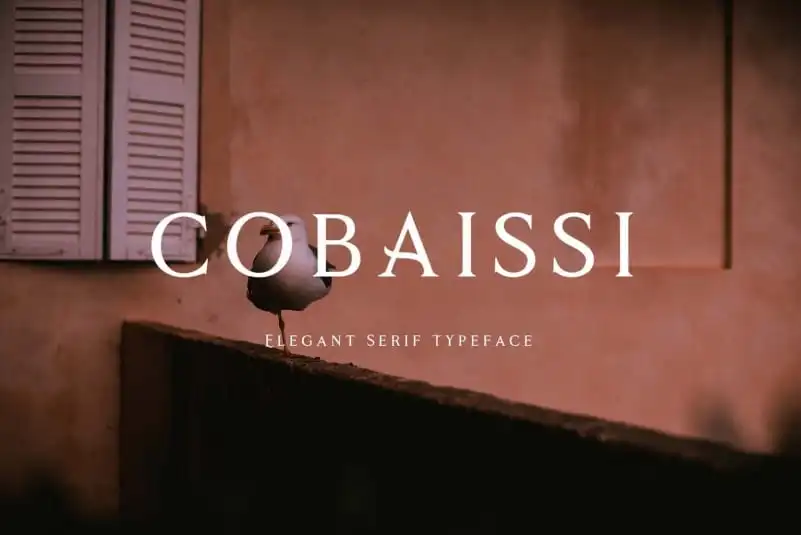
A Cobaissi Serif Font é uma elegante fonte romana moderna, projetada para ser usada tanto no design gráfico quanto na criação de logotipos ou masthead’s. Seus traços arredondados suaves e gílios com alta contraste a tornam ideal não apenas para uso em corpo de texto, como também para criações visuais interessantes. Suas curvas suaves e elegantes permitem um toque feminino sem perder seu poder robusto e moderno. Perfeita para layouts que precisem de uma fonte romana com alma e profundidade. A Cobaissi também oferece supprot multilíngue, tornando-a ainda mais versátil e universal. Seja para usar em designs de quote ou em qualquer outro tipo de layout gráfico onde a presença elegante de um bom tipo de letras romana seja desejada, esta fonte não deixará você decepcionado. É uma escolha inteligente para quem busca uma fonte de qualidade que se destaca tanto na tipografia quanto nos logotipos. Não importa o uso que você lhe dê, a Cobaissi Serif Font oferece um equilíbrio perfeito entre elegância e robustez, tornando-a uma opção imperdível para qualquer designer.